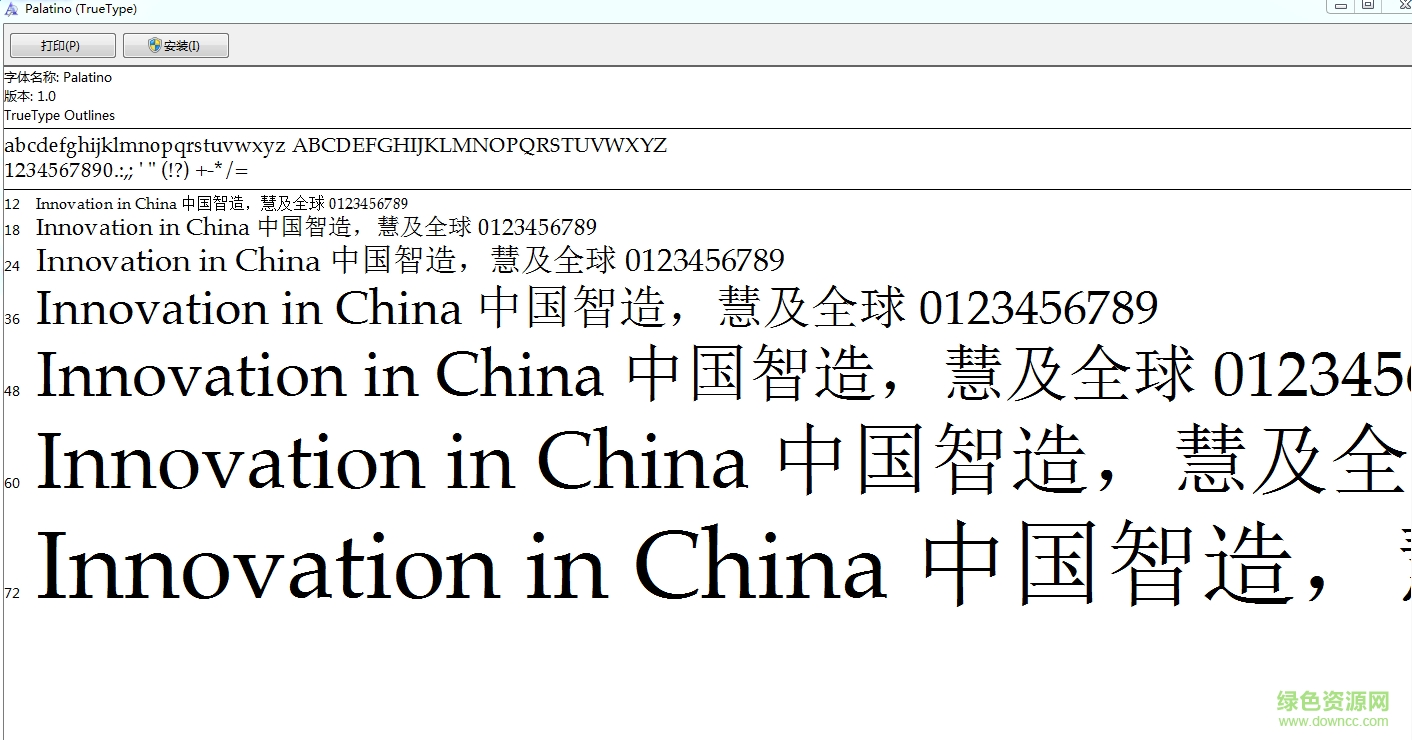
palatino字體是一款好看的英文襯線字體,筆勢(shì)走向流暢,筆末較細(xì),辨識(shí)度高,排版便捷,小編為提供提供了詳細(xì)的字體安裝方法,歡迎大家在綠色資源網(wǎng)下載!
在傳統(tǒng)的正文印刷中,普遍認(rèn)為襯線體能帶來(lái)更佳的可讀性(相比無(wú)襯線體),尤其是在大段落的文章中,襯線增加了閱讀時(shí)對(duì)字母的視覺參照。而無(wú)襯線體往往被用在標(biāo)題、較短的文字段落或者一些通俗讀物中。相比嚴(yán)肅正經(jīng)的襯線體,無(wú)襯線體給人一種休閑輕松的感覺。隨著現(xiàn)代生活和流行趨勢(shì)的變化,如今的人們?cè)絹?lái)越喜歡用無(wú)襯線體,因?yàn)樗麄兛瓷先ァ案蓛簟薄?/p>